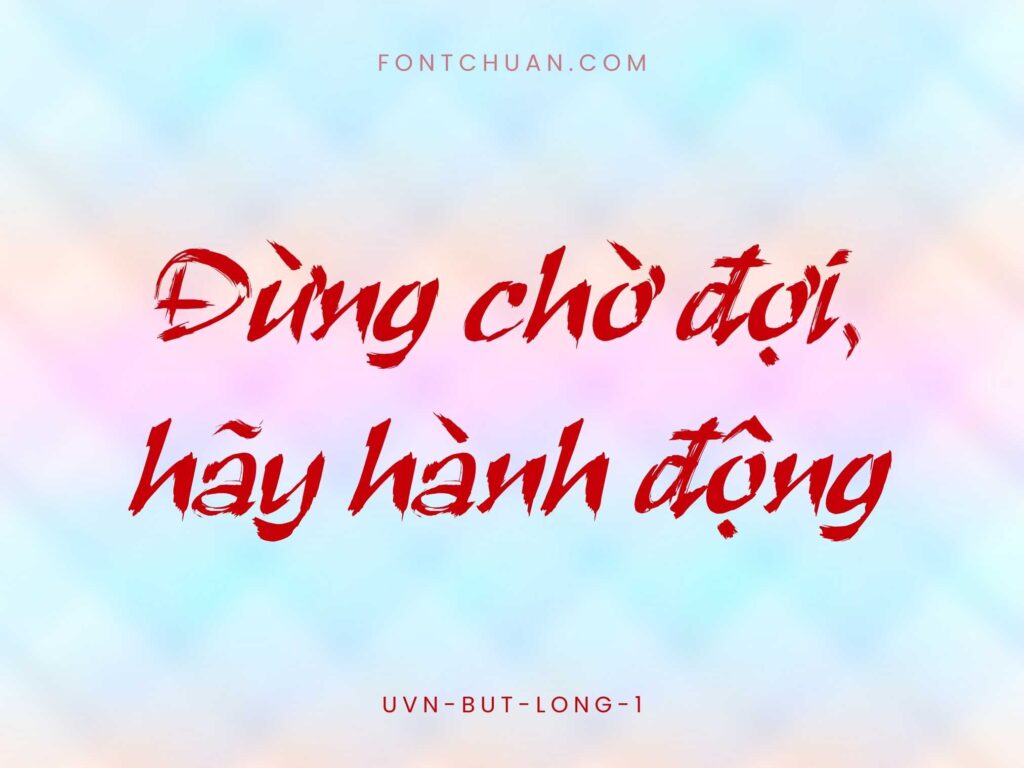
Font UVN But Long 1 Việt Hóa
UVN Bút Lông 1 là một Font chữ thư pháp mang đậm phong cách nghệ thuật viết tay truyền thống. Được thiết kế với các nét bút lông mềm mại và uyển chuyển, phông chữ này tạo nên sự thanh thoát và tinh tế cho các tác phẩm thiết kế. UVN Bút Lông 1 hỗ trợ đầy đủ các ký tự tiếng Việt, giúp người dùng dễ dàng sử dụng trong các dự án sáng tạo liên quan đến văn hóa Việt Nam. Phông chữ này không chỉ phù hợp cho các thiết kế mang yếu tố văn hóa Việt mà còn được nhiều nhà thiết kế yêu thích sử dụng như một Font chữ ảnh cưới để tạo nên cảm giác lãng mạn, nhẹ nhàng và nghệ thuật trong các bộ thiệp mời hoặc thiết kế liên quan đến tình yêu.
Với thiết kế độc đáo và nghệ thuật, UVN Bút Lông 1 phù hợp cho các ứng dụng như thiệp mời, tiêu đề sách, thiết kế logo và các ấn phẩm nghệ thuật. Trong lĩnh vực sự kiện, phông chữ này có thể được sử dụng trong các dịp như lễ hội, lễ cưới và các sự kiện văn hóa. Ngoài ra, UVN Bút Lông 1 cũng thích hợp cho các ngành nghề như thiết kế đồ họa, nghệ thuật trang trí và xuất bản.